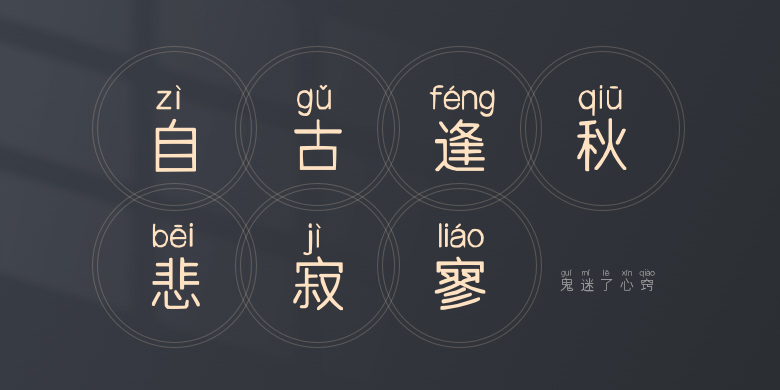
鬼迷了心窍
鬼迷了心窍,这款字体结构工整、笔画清晰,兼顾美观与易读性,适用于标题、正文、海报、包装、LOGO 等多种场景。字形优雅稳定,风格百搭耐看,适配日常排版与创意设计,让文字呈现更舒适、更具质感。鬼迷了心窍一笔一画,皆是细节,以均衡的比例、流畅的线条打造舒适视觉体验,字形端正大气,风格简约现代。无论是商业设计、品牌宣传还是日常排版,都能轻松驾驭,让文字更有格调与力量。鬼迷了心窍字体下载。